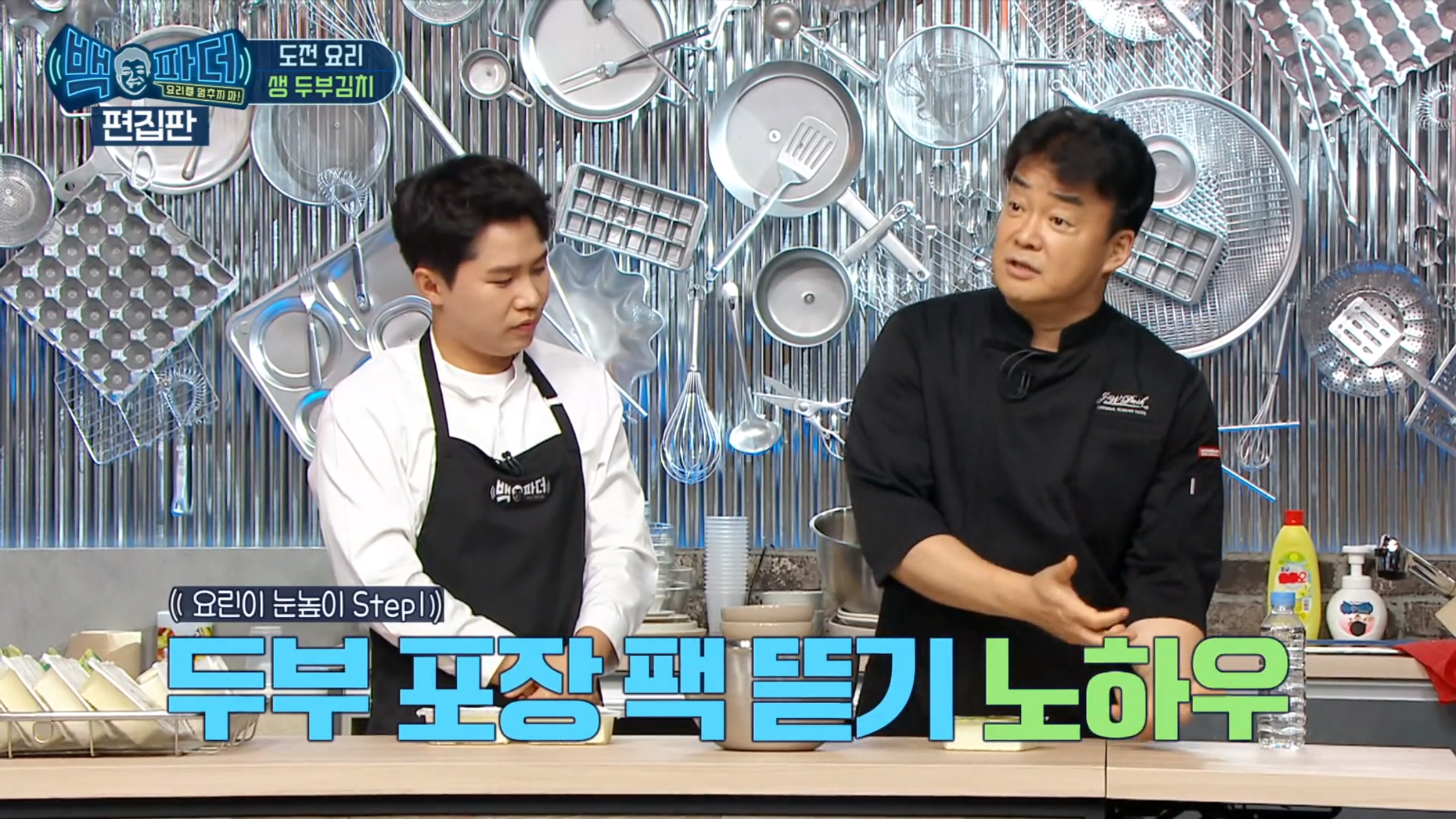
MBC에서 창사 60주년을 기념하여 'MBC 1961체' 2종을 공개하였습니다. 1961년 MBC 인사동 사옥 옛 간판을 모티브로
1960년대 모듈 형태의 간판 느낌을 현대적 디자인으로 재해석하여 개발한 제목용 폰트입니다.
글꼴은 MBC 1961, MBC 1961 굴림 폰트 2종으로 되어 있으며 제목용으로 사용하기 좋은 형태입니다.
사용 예
방송에서 영상 자막용으로도 유용한 글꼴인 것 같습니다.